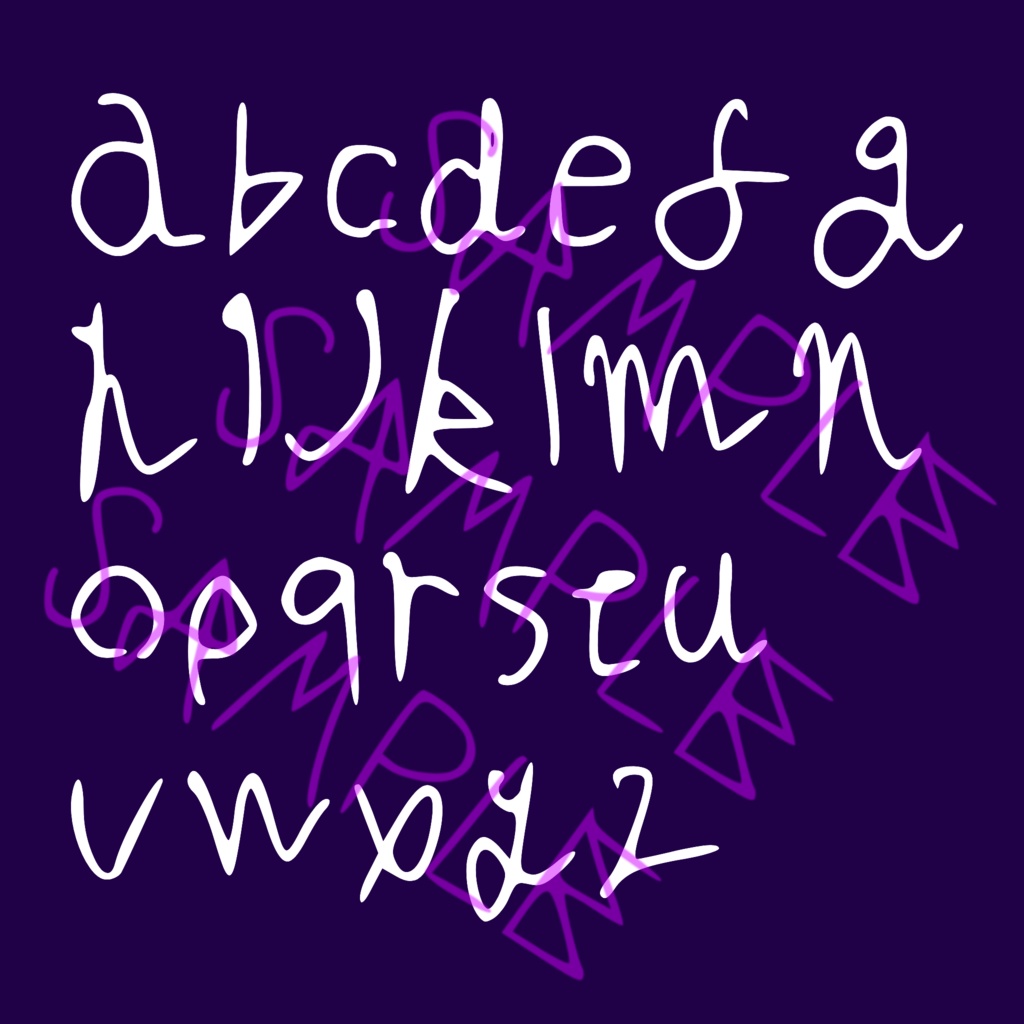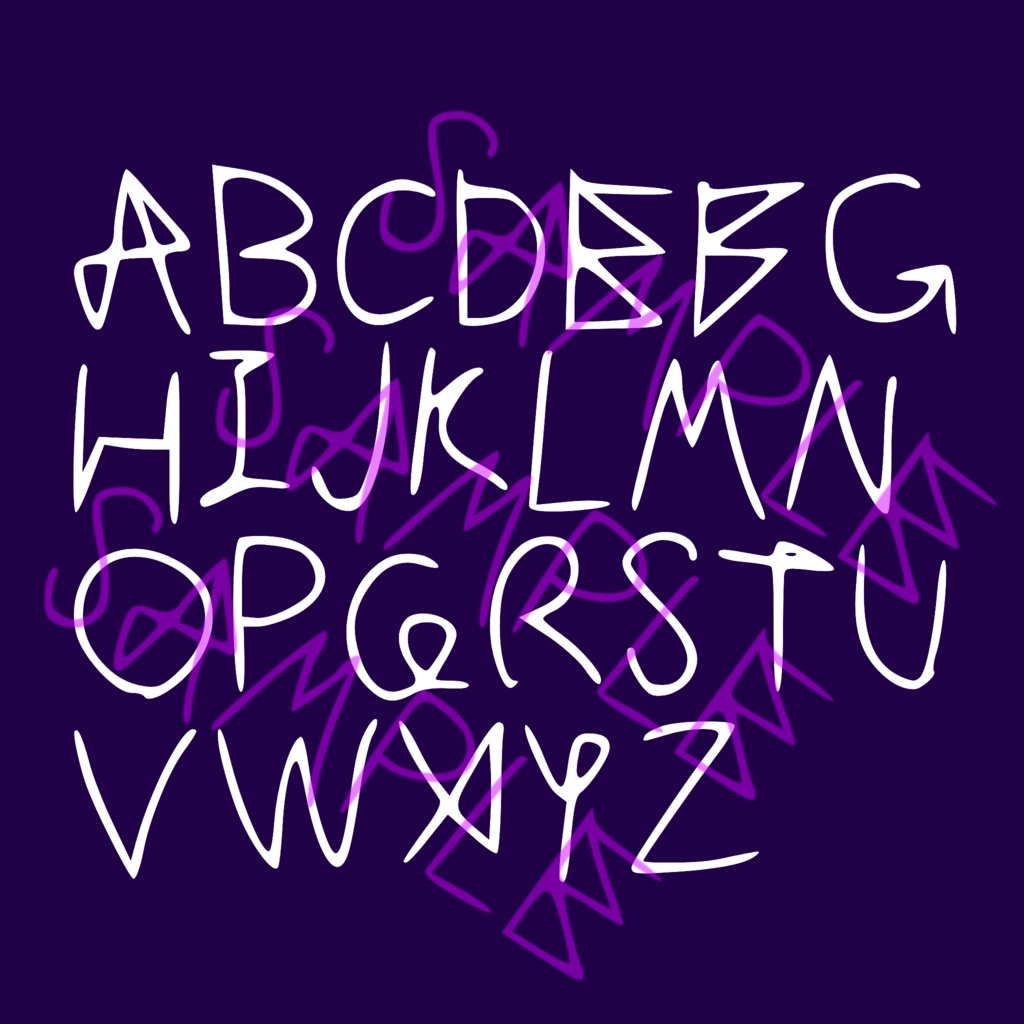
手書きフォント ENGLISH【Wilmaフォント】
【WILMA FONTS】 Wilmaフォントは、私ショップオーナーのWilmaが書いたフォントになります。 当フォントは全て一筆書きで書いています。 ファイル形式 TrueType 【収録文字】 ・大文字 小文字 アルファベット ・数字 0~9 ・記号(! ? ' " . , : ; &) 【注意事項】 ・このフォントは、個人・企業問わず、全ての方が自由に利用可能です ・フォントデータを改変、二次配布等の購入者以外が入手出来る状態にすることはやめてください。 ・著作権は私(Wilma)にありますので、商標登録や、作者を偽るような行為を行わないでください。 (簡単説明) 二次配布しなかったら基本的にどんな用途でも自由に利用してOKです。 【その他】 ・「支援版」は、通常のダウンロード版と内容が変わりません。 ・万が一ご利用にあたって何かご不明な点や不具合がありましたら、BOOTHのメッセージをよろしくお願いいたします。